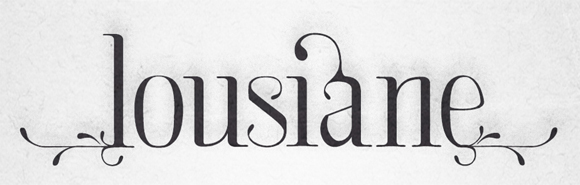
El diseñador, ilustrador y tipógrafo Juan José Rivas, hace poco que ha remozado su sitio web y para celebrarlo ha puesto a disposición de sus visitantes algunas tipografías gratuitas. En este caso hablamos de Lousiane, una tipografía «art nouveau» con numerosos detalles orgánicos, contrastes y formas que hacen de la misma el complemento perfecto para un trabajo en el que la tipografía vaya más allá de la transmisión de un texto y se necesite cierto aporte «connotativo». Y a nosotros nos gusta la frescura que transmite esta tipografía, así como el trabajo tipográfico de Juanjo que podréis disfrutar en la galería de su web.